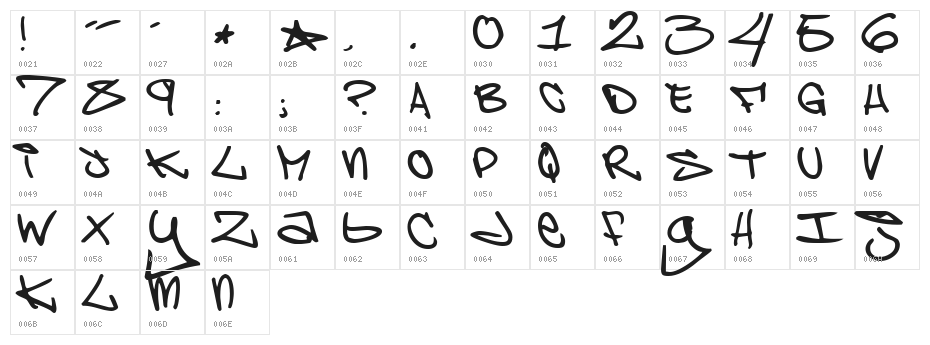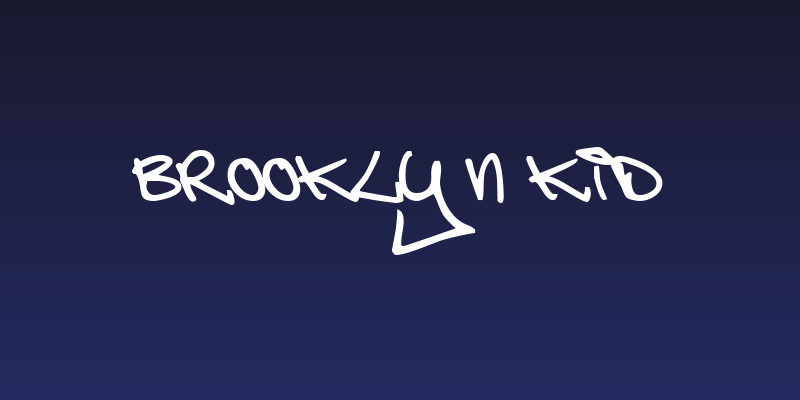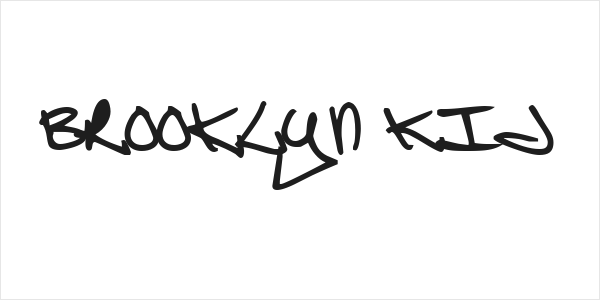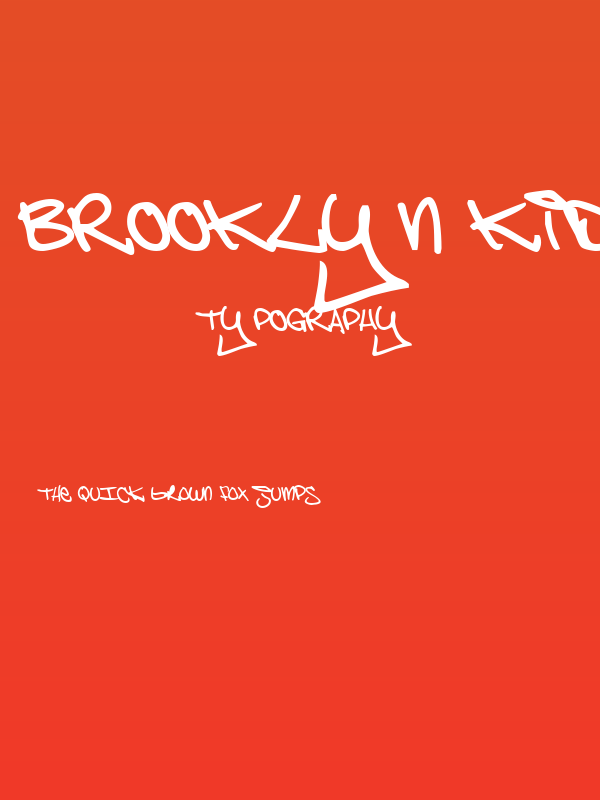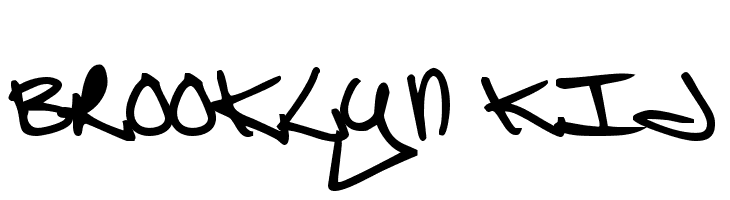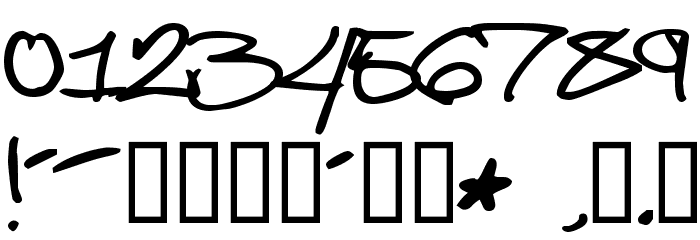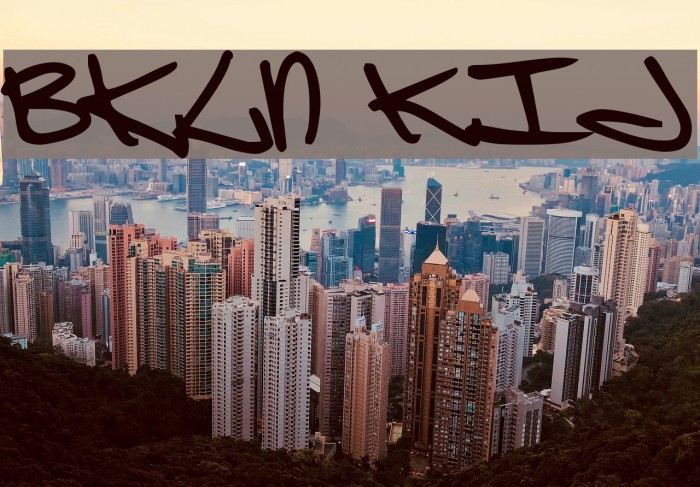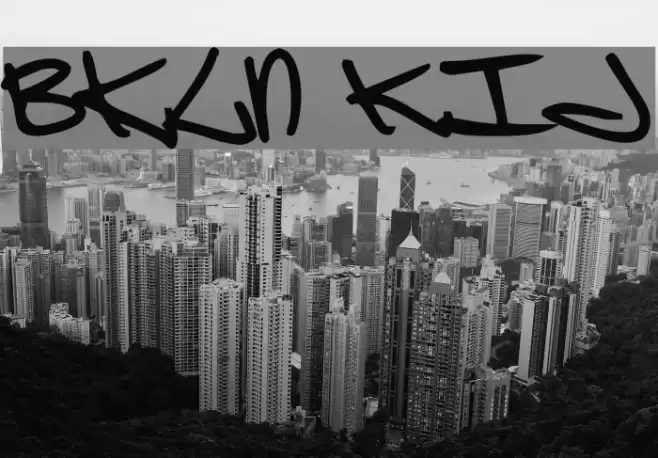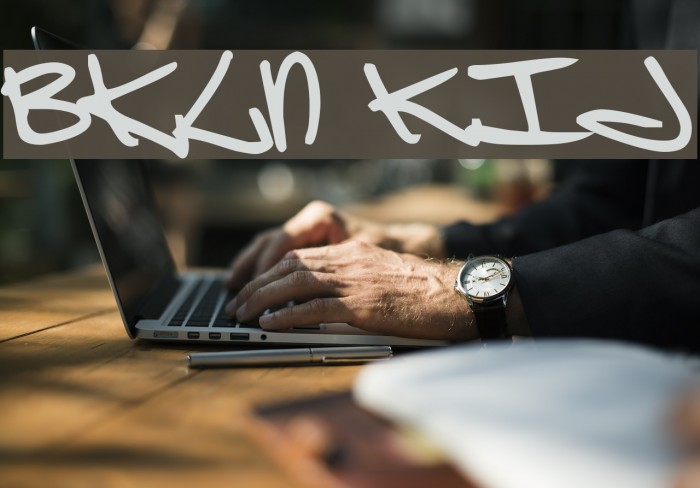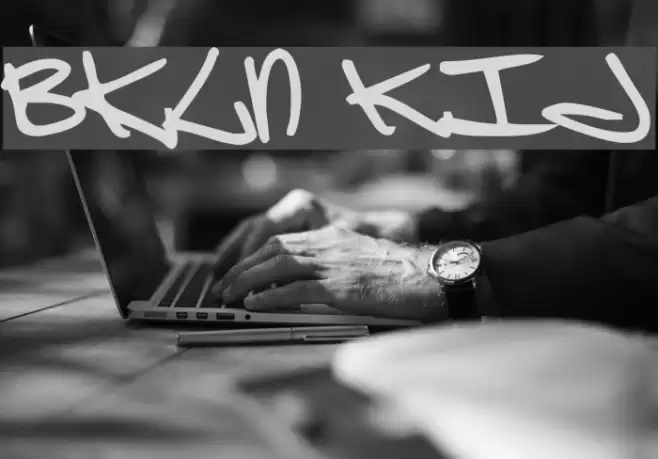
Brooklyn Kid Font
| Style général | Urban, Artistic, Edgy |
| Cas d'utilisation | Logos, Posters, Album covers |
| Projets proposés | Street art designs, music album covers, urban-themed posters, and edgy branding projects. |